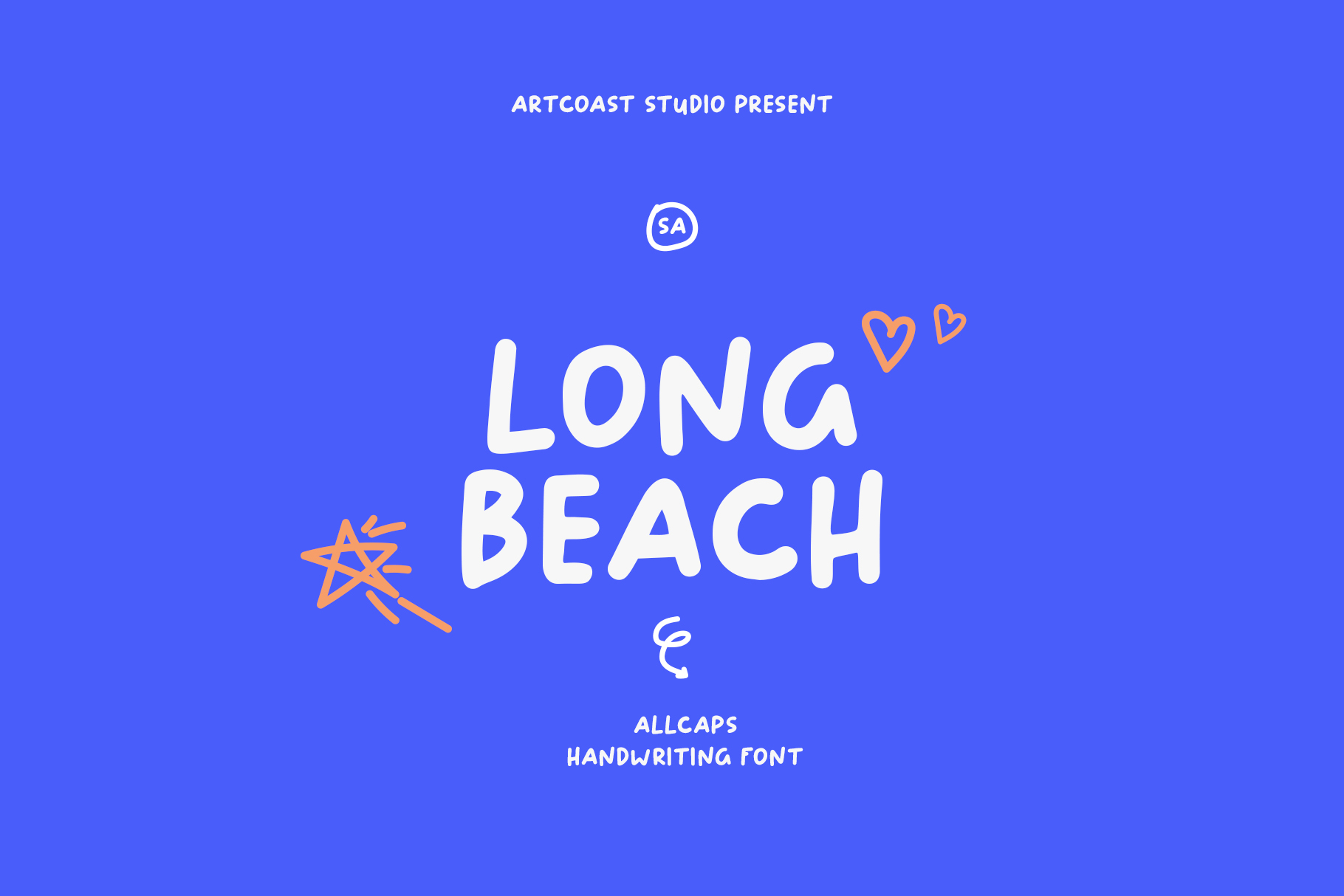
SA Long Beach Рукописный шрифт с поддержкой кириллицы
"SA Long Beach" – это шрифт, который выделяется своей красотой и индивидуальностью. Его мягкие, закругленные и изогнутые буквы воплощают в себе уют и доброту, придавая вашей работе мягкость и веселье. Этот шрифт идеален для дизайна, который требует создания уютной и привлекательной атмосферы.